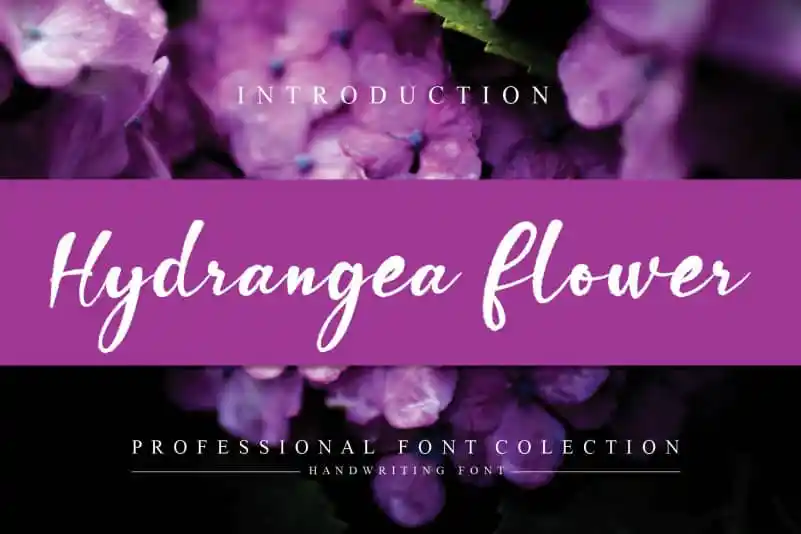
Hydrangea Flower Script Font – Download Grátis
A Hydrangea Flower Script Font é uma elegante e moderna fonte escrita a mão que traz à tona os melhores elementos do estilo calligráfico. Suave e fluida, esta fonte se destaca por sua delicadeza e beleza natural, tornando-a perfeita para qualquer projeto de design. Seja ela usada em letras grandes em uma capa ou em detalhes sutis em um brochura de artes gráficas, a Hydrangea Flower Script Font irá transformar seu trabalho de forma clara e sofisticada, sem nunca perder sua elegância única. Ela se destaca entre outras fontes para quem valoriza a paleta de cores suaves e o charme dos traços leves e fluidos do estilo calligráfico. A Hydrangea Flower Script Font é uma escolha natural para projetos que buscam expressar beleza, delicadeza e um toque pessoal em cada letra impressa.